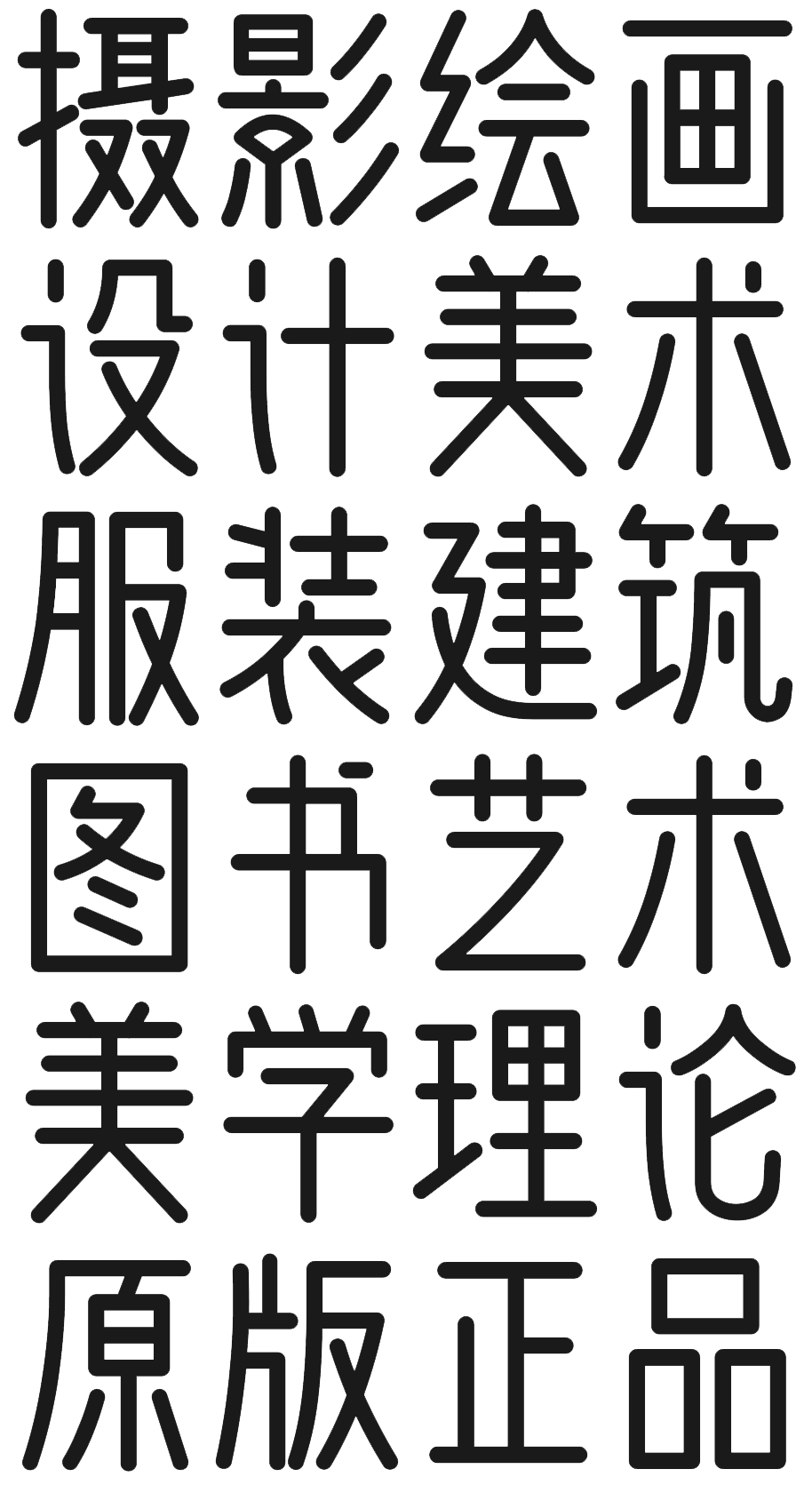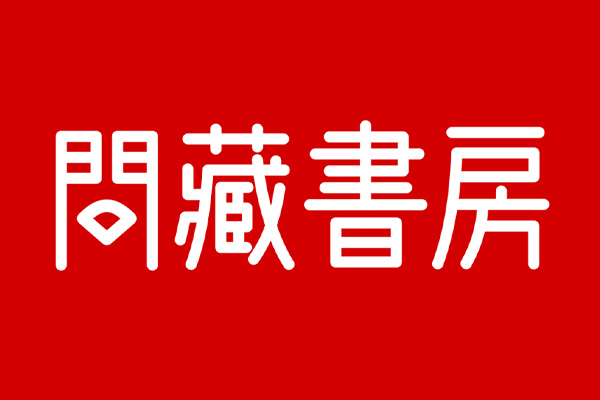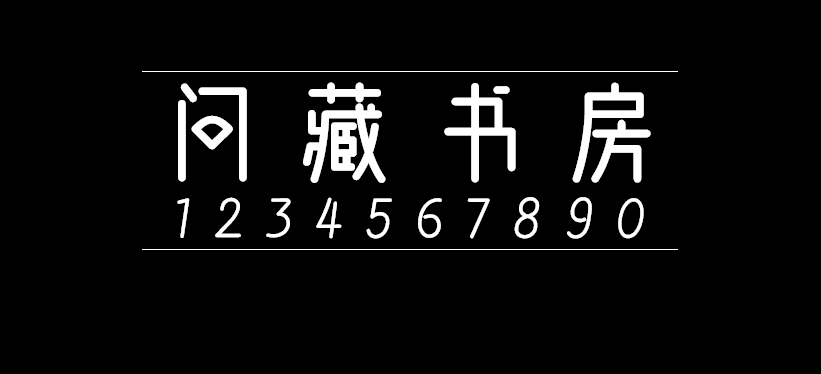
问藏书房
问藏书房联合造字工房一起,以始终如一的原创精神,精心打造了一款字体产品“问藏书房”字体,在建国七十周年之际,开源给中国大陆地区一切个人与商业机构免费使用,以感谢国家给予的所有权益政策,感恩回馈一路支持正版字体的客户和朋友! 问藏书房字体的设计整体现代简约,中宫紧凑,视觉阅读极具层次感,字字俊秀且呈现古雅之风,设计团队以精心的设计赋予了汉字全新美感!字符编码采用中华人民共和国GB2312-80字符集标准,按需添加101个汉字。共收容字数6864CJK汉字,ASCII常用字符100个。